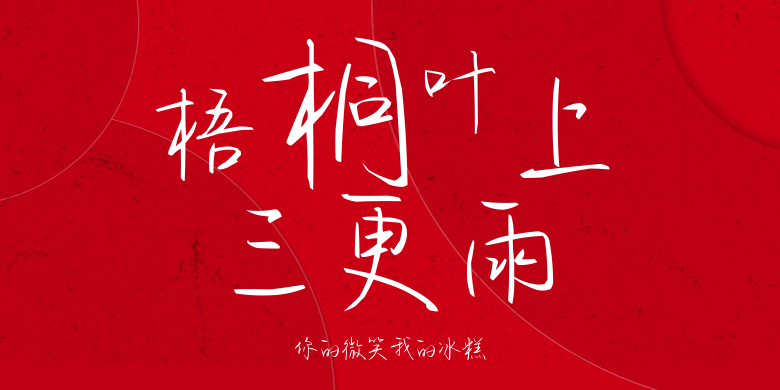
你的微笑我的冰糕
你的微笑我的冰糕,这款字体结构工整、笔画清晰,兼顾美观与易读性,适用于标题、正文、海报、包装、LOGO 等多种场景。字形优雅稳定,风格百搭耐看,适配日常排版与创意设计,让文字呈现更舒适、更具质感。你的微笑我的冰糕一笔一画,皆是细节,以均衡的比例、流畅的线条打造舒适视觉体验,字形端正大气,风格简约现代。无论是商业设计、品牌宣传还是日常排版,都能轻松驾驭,让文字更有格调与力量。你的微笑我的冰糕字体下载。